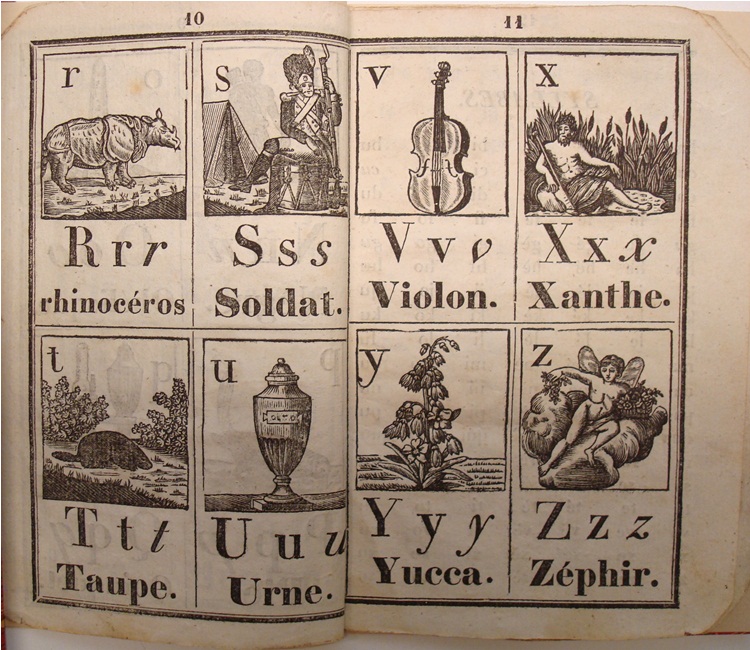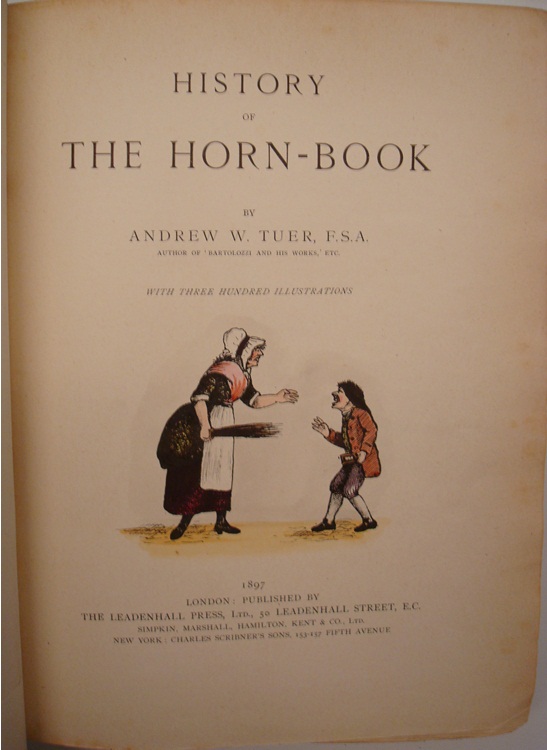
| Detalle de "History Of the Hornbook" A. Tuer: London, 1897. |
| Clase de religión y lectura. Nikolaos Glikós: Venecia, 1789. |
Unos abecedarios de diferentes países de la segunda mitad del XIX:
"Abécédaire du Chrétien Religieux" Editíon augmentée de 26 gravures. Paris: Chez Delarue, sin fecha.(s.XIX). 8º. 36 páginas que incluyen abecedarios, silabario, pequeña formación del mundo y unas tablas de multiplicar.
Elemental librillo para aprender a leer mínimamente y conocer las letras.
| Portada |
"PANORAMIC ALPHABET, Second Series". Leeds: Weeb & Millington, circa 1860. 8º. 24 láminas.
Bonito abecedario con una ilustración coloreada para cada letra.
| Portada |
Un libro para aprender a escribir y leer:
FERDINAND HIRTS."Deutfches Lefebuch". Breslau: F. Hirt, 1901.4º. 96 páginas.
Método de escritura y lectura con muchas ilustraciones y textos.
| Portada |
Hablemos de HORNBOOKS:
TUER, A." History of the Horn Book". London: The Leaden Hall Press, 1897. Segunda Edición.
4º, 486 páginas, dos folios, 3 reproducciones de hornbook dentro del mismo libro.
Magnífica historia del hornbook publicada por Tuer. Estas pequeñas tablillas con el abecedario eran utilizadas en Inglaterra para que los niños aprendieran a nombrar las letras y los números. Seguramente se introdujo esta práctica a partir de 1450 y se utilizó plenamente en el s. XVI. El libro que nos ocupa es de los "especiales" ya que al final tiene una caja incorporada con 3 reproducciones de hornbook. (La primera edición en dos volúmenes de este libro incorporaba 7 reproducciones de hornbooks). Una de las cosas a destacar a parte del texto es la importante cantidad de ejemplos e ilustraciones sobre el tema. Libro esencial e imprescindible. Hay un artículo sobre el autor en Wikipedia muy ilustrativo: http://en.wikipedia.org/wiki/Andrew_White_Tuer
| Portada |
Ejemplos de Hornbook de elegantes decoraciones:
| Molde de Hornbook |
| Abecedario de papel |
| Facsímiles de Hornbook Cara 1 |
| Facsímiles de Hornbook Cara 2 |
Diferentes ilustraciones del libro que contienen escenas con hornbook:
PLIMPTON, G. A. "The Hornbook and Its Use in America". Artículo editado en la revista "American Antiquarian Society" el octubre de 1916. Va de la página 264 hasta la 272 y contiene 10 páginas de láminas con ilustraciones.
Este artículo es interesante porqué fecha el inicio del uso de los Hornbooks un poco antes, a partir de finales del s.XIV y habla de su introducción en América del Norte. Las láminas son ejemplares.
El autor de este artículo fue un gran coleccionista de libros y manuscritos famoso por su increíble colección sobre las matemáticas (ver este artículo: http://www.historyofscience.com/articles/plimpton-elementary-mathematics.php)
| Portada |
| Manuscrito de aritmética de Sacrobosco, (1400) donde un monje enseña con un hornbook a un niño |
Ejemplos de Hornbook para leer y contar:
ADENDA: después del comentario de nuestra amiga Claudia E. Troncoso e intentando encontrar una posible traducción de este termino os explico el porqué de este curioso nombre en inglés según el mismo Tuer: Horn en inglés se aplicaba a un recubrimiento hecho de una fina capa de asta o cuerno animal que era parecida a lo que ahora es el plástico, se utilizaba mucho en Inglaterra para construir tabaqueras, cajitas botones etc... y como no para proteger la fina lámina de papel en que se había imprimido el abecedario los números y generalmente una oración. Esta lamina de" horn" se aguantaba con un pequeñito marco clavado. Si miráis arriba hay unos ejemplos muy claros de estos hornbooks. De aquí su especial nombre.
ResponderEliminarDesconocía el uso de los hornbook. Un artículo
muy interesante.
Grácias Marisa, el tema "Hornbook" es todo un mundo a parte y propio de los países anglosajones, aquí se ha utilizado siempre la pizarra y la tiza y por supuesto los abecedarios y silabarios.
Estimado Marcos:
ResponderEliminarme ha gustado mucho tu artículo, me gustaría saber, si lo sabes, una traducción al español para, hornbook, desde ya te lo agradezco.
Pues, como te he explicado en un mail a parte creo que es mejor utilizar la misma en ingles ya que no existe en castellano ninguna que se pueda parecer. Es parecido a termino "whisky" y muchas otras que se utilizan directamente. Por ejemplo el "Chotis" ,baile madrileño, es una abreviación de "Scottish" baile escocés que se popularizó a finales del XIX esté si que se tranformó adaptandolo, pero en el caso de Hornbook nunca que yo sepa se utilizó en España de manera que es inexistente. Si te atreves tu...